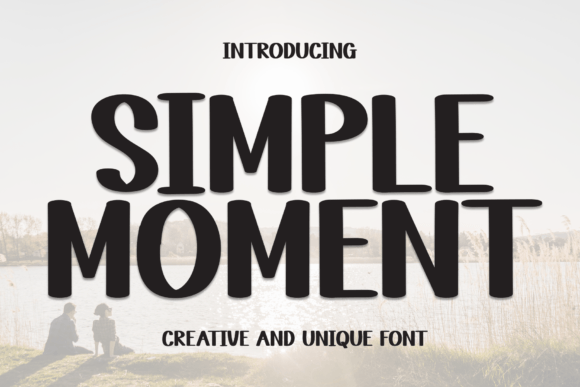
Simple Moment Font
Simple Moment Font – خط أنيق وعصري يتميز بتصميمه البسيط والمميز، مما يجعله مثاليًا للمشاريع الإبداعية. سواء كنت تعمل على تصميم شعارات، دعوات، منشورات وسائل التواصل الاجتماعي، أو حتى تصاميم العلامات التجارية، فإن هذا الخط يضيف لمسة من الأناقة والوضوح إلى أعمالك.
يتميز Simple Moment Font بحروفه المتناسقة وسهولة قراءته، مما يجعله خيارًا رائعًا للمصممين والمبدعين الذين يبحثون عن خط يعكس البساطة والرقي في آنٍ واحد. احصل عليه الآن وامنح تصاميمك طابعًا فريدًا وجذابًا!